量産型オタクが愛用する日本語フリーフォントまとめ
今回は、「量産型オタク・地雷系オタク」が愛用するよっても可愛いおすすめのフリーフォントをまとめてみました。
タグ画像・オリジナルキンブレシートなどの推し活グッズで使える人気の高いフォントをご紹介します!
「どのフォントを使えばかわいい物が作れるかな?」「可愛いフォントないかな?」と悩んでいる方におすすめフォントをご紹介します。
「量産型オタク」におすすめフリーフォントのまとめ
量産型オタクに人気で定番のフォントばかりです。漢字・ひらがな・カタカナも使えるフォントばかりなので、幅広いシーンで活躍するフォントです。
本記事で紹介しているフォントの一部ですが、応援うちわに取り入れてみるとこんな可愛い仕上がりになるフォントばかりなので、ぜひ参考にしてください。
【定番】ましゅまろポップ ハート
ましゅまろポップ ハートフォントは、ぷっくり膨らんだ文字の中にハートが散りばめられているかわいいフォントです。
ハートのイラストが文字に入っていることで、アイドルやアーティストの名前で使うと、とっても可愛い印象になります。
【定番】にくまる
にくまるフォントは、ムニュッとと押しつぶしたような、ゆるくて愛らしく可愛らしいデザインになっています。
推し活グッズを手作り人に人気で量産型オタクで利用されている方が多いフォントの1つです。
【定番】Cherry Bomb
Cherry Bombフォントは、プクプクとした手書き感のある文字が可愛らしいかな文字フォントです。オタ活グッズ制作界隈で人気フォントの1つです。
【定番】みんとキッスんとキッス
みんとキッスフォントは、切り込みと光沢が入っている目立つフォントです。
とっても人気の高いフォントですが、その理由は、シンプルでかつ太さがある可愛いフォントだからです。ライブ会場などの遠くからも読める文字となっているフォントです。漢字が含まれていないフォントなので、ひらがな・カタカナに使いたい人におすすめです。
【定番】チェックポイント★リベンジ
チェックポイント★リベンジフォントは、独特の極太の太さのバランスをもち、文字の線の太さのバランスなどできるだけ統一された少しポップでユニークなフォントです。
太さとインパクトありますが、角丸処理がいるので、柔らかい印象があるフォントです。
ななキュンのうた
ななキュンのうたフォントは、「音符」や「ハート」が隠れている可愛らしいデザインフォントです。
使用する文字によって雰囲気がガラッと変わるので、量産型オタクが見ていて楽しめるフォントです!
キルゴUフォントは、太さが極太で、ゴツゴツとしたインパクトもあるので、量産型オタクにぴったりなフォント!
画数が多い漢字の名前に使う場合は、少し潰れた印象がでてしまう可能性があるので、ひらがな・カナカナを使ってみるのがおすすめです!
【王道】けいふぉんと
けいふぉんとは、スタンダードなゴシック体タイプですが文字もちょうどよい太さで読みやすく、少し動きがあるので可愛らしい、そのため使いやすいフォントです。オタ活グッツやオタ活動画制作などさまざまなシーンおいて定番で、人気のあるフォントです。
どきどきファンタジア
どきどきファンタジアフォントは、太めの丸ゴシックに、ツヤ表現の装飾がついたユニークでデザインです。ネームボードや推し活うちわなどのデザインで大きめの文字に使うのがおすすめです!
トガリテ
トガリテフォントは、トゲが生えているようなデザインが結構目立つフォント。
トゲの装飾が、K-POPや韓流系アイドルなどのカッコいい&可愛いを印象付けるフォントです。他の人と被りづらいフォントを探している方にぴったりなフォントです。
くらむぼん
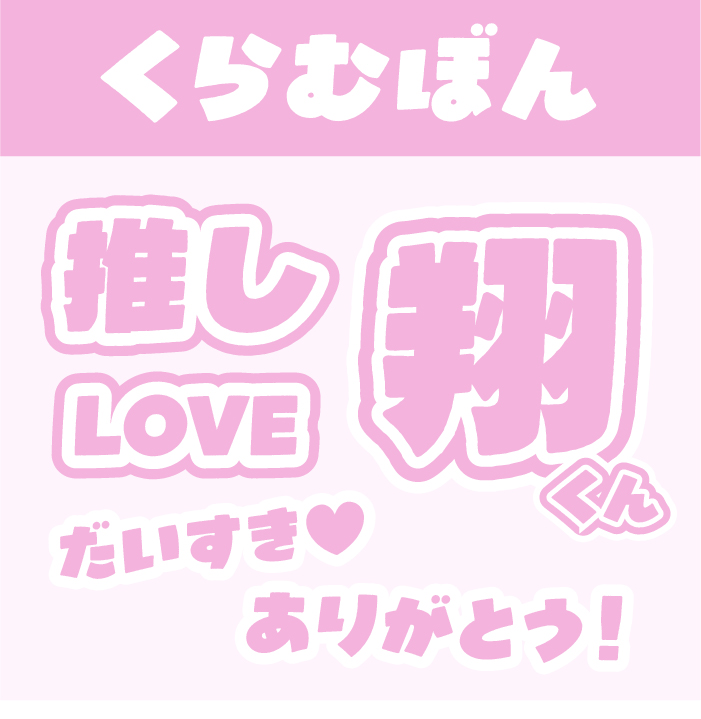
くらむぼんフォントは、デラゴシック(DelaGothic)を膨らませて、ギザギザな処理を施し、ボンッと動きがあるとても可愛らしいフォントです。太さもあるので、インパクトや目立つフォントとなっているので、応援うちわとかでも活躍できます。
源暎きわみゴ
源暎きわみゴは、ダイナミクスに作られている超極太ゴシックです。インパクトがあるけど視認性や判読性も高く推し活グッツ制作などにぴったりなフォントです。
カタカナボーイ
カタカナボーイフォントは、元気な印象があるフォントです。カタカナのみですが、Y2Kや2000年代的なレトロな印象があるフォントです。
ニクキュウ
ニクキュウフォントは、プクプクと膨らみがある文字に加えてキラッと光るツヤのあるカタカナフォントです。とっても可愛フォントです。
【定番】コーポレート・ロゴ(ラウンド)
コーポレート・ロゴ丸フォントは、太さがあり、インパクトもあるので量産型オタクの方に人気のある丸ゴシックフォントです。
崩しすぎていないの文字の読みやすさもあり、ほどよいシャープさもあるので、可愛くなりすぎないちょうど良いフォントです。
プイッコ
プイッコフォントは、マジックで書いたような極太で、線幅がランダムになっている遊びココロが満載なデザインになっています。
Mike(づにのい)
Mike(づにのい)フォントは、プクッと膨らんだ文字のアンバランス感が逆に愛らしいで、素敵なフォントです。
ノンビット(Nonbit)
ノンビット(Nonbit)フォントは、レトロゲームな雰囲気があり、可愛さもあり、インパクトもあり、オタ活では珍しいフォントなので、他の人と被りたくないといった方にもおすすめフォントです。